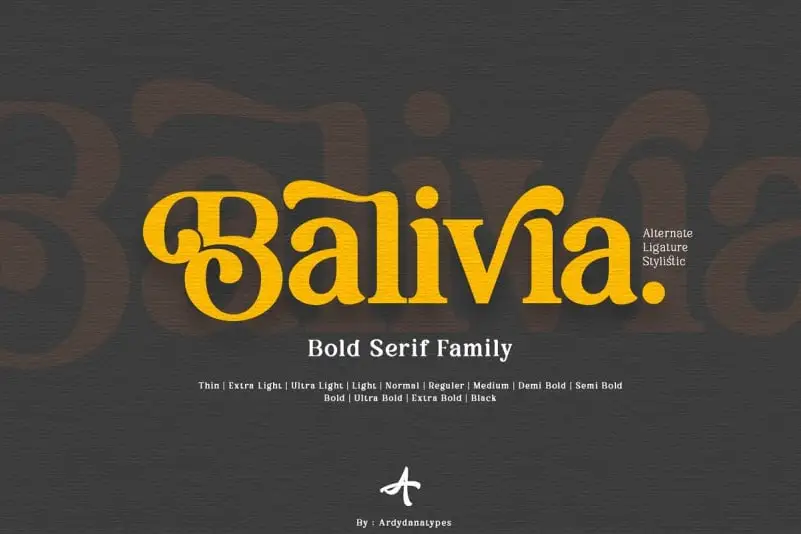
Balivia Serif Font – Download Grátis
A Balivia Serif é uma fonte serifa que traz ao design uma dose de elegância clássica moderna, enquanto mantém a sensação única e sofisticada dos tempos atuais. Desenhada pelo designer Ardyanatypes na plataforma 99designs, esta fonte oferece uma gama de opções desde o fino até o bold, garantindo inúmeras possibilidades para utilizá-la em diversos projetos gráficos. Com seus traços fluidos e sutis curvas, a Balivia Serif não apenas combina harmoniosamente com estilos antigos, mas também traz um toque moderno que é imperceptível. Seu destaque são as ligaturas, elementos criados por conectarmos graficamente dígrafos em uma única linha de escrita, resultando em linhas finas e elegantes que se integram perfeitamente à tipografia serifa. A fonte traz um toque especial aos seus projetos, apresentando um visual atraente e moderno sem perder o charme do estilo clássico. Seja você criando uma identidade visual, desenvolvendo um site ou simplesmente trabalhando em materiais de marketing digital, essa fonte é perfeita para dar seu projeto aquele toque especial que torna a diferença. Com suas opções variadas e ricas em detalhes, a Balivia Serif oferece à você muitas possibilidades para criar um design único e memorável.